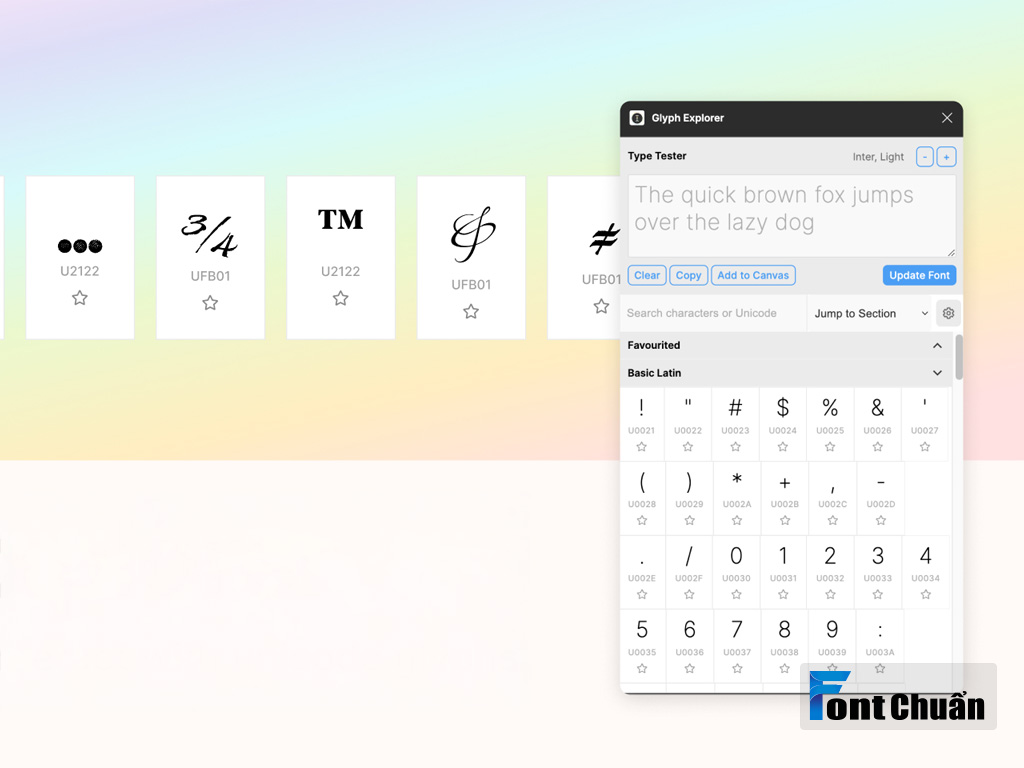
Ẩn sau mỗi ký tự bạn gõ là một thế giới hình ảnh phức tạp trong font chữ. Thành phần cốt lõi tạo nên văn bản chúng ta thấy chính là glyph – hình ảnh cụ thể của một chữ. Khác với “ký tự” (character) là khái niệm trừu tượng , glyph là biểu diễn đồ họa hữu hình trong một font nhất định. Công nghệ OpenType hiện đại cho phép một font chứa hàng ngàn glyph, bao gồm các biến thể, chữ ghép, và ký hiệu. Bài viết này của Font Chuẩn sẽ giúp bạn giải mã “glyph là gì?”, khám phá sự đa dạng, mối quan hệ với font, typeface, và vai trò không thể thiếu của chúng trong thế giới typography hiện đại.
Định nghĩa thuật ngữ “Glyph”
Để hiểu rõ về typography và cách văn bản được hiển thị, việc nắm vững định nghĩa về glyph là điều cần thiết.
Định nghĩa Cốt lõi
Trong typography và khoa học máy tính, glyph là hình ảnh cụ thể đại diện cho một ký tự trong hệ thống chữ viết. Đó là hình thức hiển thị hữu hình – như nét mực in trên giấy hay điểm ảnh trên màn hình – giúp người dùng đọc được văn bản.
Nguồn gốc và Bối cảnh Lịch sử
Thuật ngữ “glyph” bắt nguồn từ tiếng Hy Lạp glyphē, nghĩa là “khắc”, phản ánh nguồn gốc ban đầu của nó trong các nền văn hóa cổ đại như Ai Cập và Maya, nơi ký hiệu được chạm khắc trên vật liệu cứng. Ngày nay, glyph tồn tại dưới dạng số hóa trong các file font như TrueType hay OpenType.
Phạm vi trong Typography
Trong thiết kế font hiện đại, glyph không chỉ là chữ cái và chữ số, mà còn bao gồm dấu câu, ký hiệu toán học, biểu tượng và các biến thể hình thái của một ký tự (alternate glyphs). Mỗi hình dạng – dù truyền tải cùng một ý nghĩa – đều được xem là một glyph riêng biệt, làm rõ vai trò của glyph như đơn vị hình ảnh cơ bản nhất trong hệ thống chữ viết số hóa.
Glyph đại diện cho hình dạng cụ thể của ký tự. Trên nền tảng đó, variable fonts cho phép các glyph biến đổi theo nhiều trục khác nhau.
Glyph vs. Ký tự (Character): Sự Khác biệt Cốt lõi
Việc phân biệt glyph và character (ký tự) là yếu tố cốt lõi để hiểu cách văn bản được hiển thị:
Ký tự là một đơn vị ngữ nghĩa trừu tượng – như chữ cái ‘A’, số ‘7’ hay ký hiệu ‘$’. Trong máy tính, mỗi ký tự được mã hóa bằng một code point duy nhất theo chuẩn Unicode, giúp đảm bảo tính tương thích và nhất quán giữa các hệ thống.
Ngược lại, glyph là biểu hiện hình ảnh cụ thể của ký tự đó – chính là hình dạng đồ họa bạn nhìn thấy trên màn hình hay bản in. Một ký tự có thể có nhiều glyph khác nhau, tùy theo typeface, style (italic, bold…) hoặc các tính năng OpenType như alternate glyphs và ligatures.
Ví dụ:
- Chữ ‘a’ thường có thể hiển thị dưới dạng hai tầng (double-storey) hoặc một tầng (single-storey).
- Chữ ‘A’ hoa có thể xuất hiện dưới dạng chữ thường, chữ hoa nhỏ (small caps) hoặc kiểu hoa mỹ (swash).
Ở chiều ngược lại, một glyph cũng có thể đại diện cho nhiều ký tự, như chữ ghép ‘ffi’, vốn kết hợp ba ký tự riêng biệt để tăng tính thẩm mỹ và tránh lỗi hiển thị.
Trong các hệ thống có dấu phụ như tiếng Việt hoặc tiếng Thổ Nhĩ Kỳ, glyph có thể là:
- Dạng ghép sẵn: (precomposed), ví dụ ‘à’ là một glyph duy nhất.
- Dạng tổ hợp: kết hợp giữa glyph nền (a) và glyph dấu (dấu huyền), căn chỉnh bằng mark positioning trong OpenType.
Glyph trong mối quan hệ với Font và Typeface
Để hiểu rõ vai trò của glyph, cần xác định mối quan hệ giữa nó với typeface và font trong cấu trúc phân cấp của typography.
- Typeface (họ chữ) là thiết kế tổng thể bao gồm tất cả các biến thể về trọng lượng (weight), độ rộng (width), và kiểu dáng (style) của một bộ ký tự. Ví dụ: Arial, Roboto hay Helvetica đều là các typeface, mang phong cách thị giác nhất quán.
- Font là một tệp kỹ thuật số cụ thể thuộc typeface, chứa tập hợp các glyph cho một biến thể cụ thể như “Bold”, “Italic” hay “Condensed”. Ví dụ, “Roboto Bold” là một font nằm trong typeface Roboto.
- Glyph là biểu diễn hình ảnh thực tế của từng ký tự trong font. Khi người dùng chọn kiểu chữ, phần mềm sẽ truy xuất tệp font tương ứng và sử dụng glyph từ đó để hiển thị văn bản.
Trước đây, các định dạng như TrueType bị giới hạn về số lượng glyph, khiến các glyph đặc biệt (small caps, ligatures, symbols) phải lưu trong các font riêng biệt. Ngày nay, với OpenType, hàng ngàn glyph có thể được tích hợp trong một tệp duy nhất, hỗ trợ các tính năng typographic nâng cao như alternate glyphs, contextual ligatures, hoặc mark positioning.
Việc nắm vững quan hệ Typeface → Font → Glyph không chỉ giúp duy trì sự đồng bộ về thiết kế mà còn tối ưu hiệu quả sử dụng font trong thiết kế đồ họa, trình bày văn bản và phát triển giao diện số.
Phân biệt Glyph, Rune và Sigil
Thuật ngữ glyph trong typography thường gây nhầm lẫn với các khái niệm như rune và sigil, đặc biệt khi xét trên nền tảng lịch sử và biểu tượng học. Việc phân biệt rõ ba thuật ngữ này giúp đảm bảo tính chính xác trong giao tiếp chuyên ngành.
- Glyph (trong typography): Là biểu diễn đồ họa cụ thể của một ký tự trong một font chữ kỹ thuật số, đóng vai trò hiển thị văn bản trên màn hình hoặc bản in. Đây là khái niệm cốt lõi trong thiết kế chữ và điện toán hiện đại.
- Rune: Là hệ thống chữ viết cổ của các dân tộc Germanic và Scandinavia, thường có hình dạng góc cạnh để dễ khắc lên gỗ hoặc đá. Về bản chất, rune là một loại glyph, nhưng có giá trị ngôn ngữ và văn hóa lịch sử riêng biệt.
- Sigil: Là ký hiệu tượng trưng mang tính biểu cảm, biểu tượng hoặc huyền bí, không nhất thiết thuộc hệ thống chữ viết ngữ âm. Ví dụ: biểu tượng phóng xạ, logo thương hiệu, biểu tượng giả kim hay con dấu hoàng gia. Sigil có thể được xem là glyph theo nghĩa rộng, nhưng không phục vụ mục đích ngôn ngữ thông thường.
Tải ngay bộ sưu tập Font Tiếng Việt đầy đủ mới nhất hiện nay: TẠI ĐÂY
Hướng dẫn Truy cập và Sử dụng Glyph trong Thiết kế và Web
Sở hữu một font OpenType với hàng nghìn glyph là chưa đủ – để khai thác tối đa giá trị, bạn cần biết cách truy cập và sử dụng chúng qua phần mềm thiết kế hoặc mã CSS.
Trong phần mềm thiết kế (Adobe)
Glyph Panel:
- Mở qua: Window > Type > Glyphs
- Xem toàn bộ glyph của font, lọc theo nhóm hoặc tính năng như: ligatures, small caps, alternates.
- Chèn glyph bằng cách nhấp đúp.
- Hiển thị biến thể glyph khi rê chuột (Adobe CC).
Character Panel:
- Truy cập nhanh các tính năng OpenType: liga, smcp, sups, subs, contextual alternates,…
Gợi ý trực tiếp:
- Khi chọn ký tự, Adobe CC có thể hiện pop-up đề xuất glyph biến thể nếu có.
Công cụ hệ điều hành
- Windows – Character Map: Xem và sao chép glyph, ít trực quan hơn phần mềm chuyên dụng.
- macOS – Font Book: Xem glyph cơ bản, hỗ trợ giới hạn tính năng OpenType.
Trên web với CSS
- font-feature-settings: Điều khiển chi tiết tính năng OpenType với mã tag:
font-feature-settings: ‘liga’ 1, ‘smcp’ 1;
- font-variant-*: Thuộc tính dễ hiểu, thân thiện SEO hơn:
font-variant-ligatures: common-ligatures;
font-variant-caps: small-caps;
font-variant-numeric: oldstyle-nums tabular-nums;
Lời kết
Qua bài viết trên của fontchuan.com, glyph là hình dạng đồ họa cụ thể mà một ký tự trừu tượng mang lấy trong font chữ. Định dạng OpenType đã cách mạng hóa việc sử dụng glyph, cho phép tích hợp hàng ngàn biến thể như chữ ghép (ligatures), số kiểu cũ (oldstyle figures), chữ hoa nhỏ (small caps), và các dạng thay thế (alternates) vào một font duy nhất. Việc sử dụng các glyph đa dạng này không chỉ làm tăng tính thẩm mỹ mà còn cải thiện độ dễ đọc và mang lại sự linh hoạt cho thiết kế. Khám phá và áp dụng chúng một cách có chủ đích sẽ giúp bạn khai thác tối đa tiềm năng của font chữ.